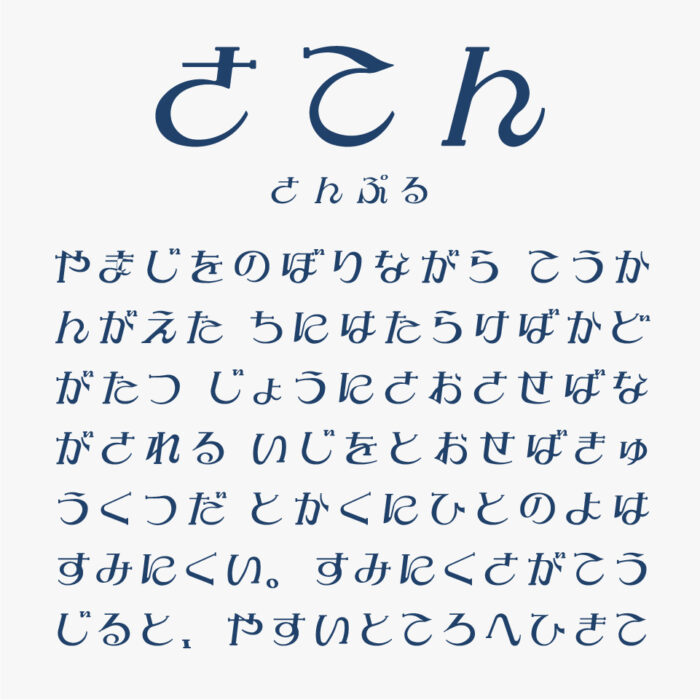
さこんフォントは、町で見かけた看板や店名の個性的で味のある文字をフォント化するプロジェクト「のらもじ発見プロジェクト」で作られれたひらがなフォントです。
装飾品店「エレガントストアさこん」の店名ロゴ。クルンとしたクセがあるカーブが文字のアクセントになっていて、文字先にちょこっと付いている飾りがとても可愛らしいデザインの昭和レトロな雰囲気を感じるとても素敵なフォントです。